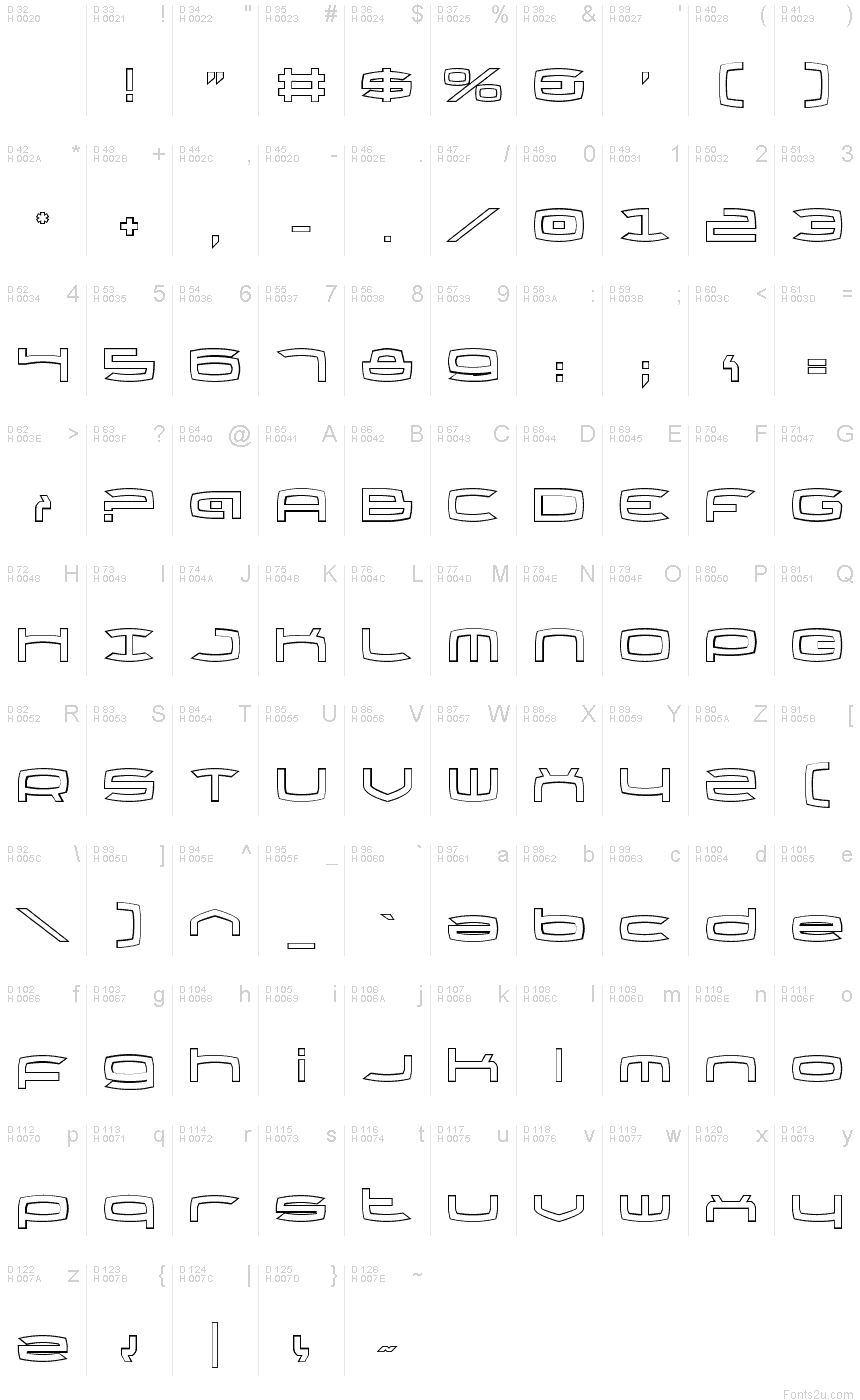
Thundergod Outline
Thundergod Outline od Iconian Fonts to darmowy, konturowy krój pisma typu display w klimacie sci-fi, z gładkim, retrofuturystycznym zacięciem. Litery są szerokie i opływowe, a dzięki zaokrąglonym rogom, długim poziomym liniom i otwartym kształtom, czcionka zyskuje spokojny, lewitujący charakter rodem z ery maszyn, zamiast surowego, industrialnego stylu.
Naturalnie odnajdzie się w logo gier, nagłówkach plakatów, okładkach albumów, planszach tytułowych i brandingu technologicznym, gdzie darmowy krój ma za zadanie wprowadzić elegancki, futurystyczny klimat bez zbędnych komplikacji. Wykorzystaj ją, gdy zależy Ci na przestrzennym, graficznym wyglądzie krótkich słów lub nazw – puste środki liter i złagodzona geometria sprawiają, że nawet proste napisy wyglądają na przemyślane i dopracowane.